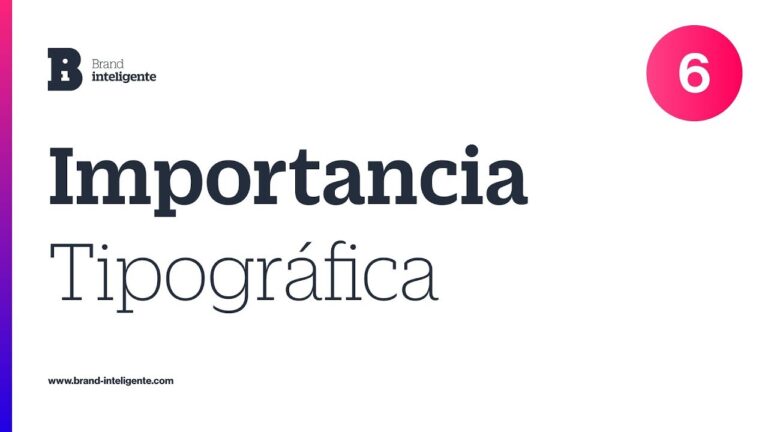
El impacto del diseño gráfico en la tipografía
El diseño gráfico juega un papel fundamental en la comunicación visual, y la tipografía es una de las herramientas más importantes en este campo. En este artículo, exploraremos el impacto que el diseño gráfico tiene en la tipografía, analizando cómo las decisiones de diseño pueden influir en la legibilidad, la estética y la efectividad de un mensaje. ¡Descubre cómo el diseño gráfico y la tipografía se complementan para crear piezas visuales impactantes!
¿Cómo influye la tipografía en el diseño gráfico?
Una tipografía bien escogida mejora la legibilidad, capta la atención del público y contribuye significativamente a la coherencia visual de una pieza de diseño. La elección de la tipografía adecuada puede transmitir emociones, reforzar el mensaje y darle personalidad a la marca o proyecto.
Además, la tipografía puede ser utilizada para jerarquizar la información y guiar al lector a través del diseño, destacando los puntos clave y facilitando la comprensión del contenido. Es importante considerar aspectos como el tamaño, el peso, el espaciado y la combinación de tipografías para lograr un resultado visualmente atractivo y funcional.
En resumen, la tipografía es una herramienta poderosa en el diseño gráfico que va más allá de la simple elección de letras. Su influencia se extiende a la comunicación efectiva, la identidad de marca y la experiencia del usuario, convirtiéndola en un elemento fundamental a tener en cuenta en cualquier proyecto creativo.
¿Qué hace un diseñador tipográfico?
Un diseñador tipográfico se encarga de dar coherencia entre imágenes, texto y formas para crear diseños equilibrados y atractivos. Prestar atención a los detalles y darles forma permite que nuestro mensaje llegue de manera rápida y efectiva a nuestros clientes, mejorando la sensación de confianza en ellos.
¿Qué es la fuente en el diseño gráfico?
La tipografía es la disposición estratégica de los tipos de estilos de letras para hacer que el lenguaje escrito sea legible y visualmente atractivo. El arte de la tipografía es una de las habilidades más importantes que todo diseñador gráfico y web debe dominar.
La influencia del diseño gráfico en la evolución tipográfica
El diseño gráfico ha tenido un impacto significativo en la evolución de la tipografía a lo largo de los años. Desde la invención de la imprenta hasta la era digital, los diseñadores gráficos han experimentado con diferentes estilos y técnicas tipográficas, influenciando directamente la forma en que se utilizan las fuentes en el diseño. La creatividad y la innovación en el diseño gráfico han llevado a la creación de tipografías únicas y modernas que reflejan las tendencias y estilos de la época.
La relación entre el diseño gráfico y la tipografía se ha fortalecido con el avance de la tecnología y la globalización. El diseño gráfico ha permitido que las tipografías evolucionen para adaptarse a las necesidades de la comunicación visual en un mundo cada vez más digitalizado. Los diseñadores gráficos han utilizado la tipografía de manera creativa para transmitir mensajes claros y efectivos, lo que ha contribuido a la evolución y diversificación de las fuentes tipográficas disponibles.
En la actualidad, la influencia del diseño gráfico en la evolución tipográfica es innegable. Los diseñadores gráficos continúan desafiando los límites de la tipografía, explorando nuevas formas de expresión visual y adaptándose a las demandas de un mundo en constante cambio. La evolución de la tipografía está estrechamente ligada al diseño gráfico, y juntos continúan moldeando la forma en que nos comunicamos a través del arte visual.
La intersección entre diseño gráfico y tipografía
El diseño gráfico y la tipografía se entrelazan de manera única en la creación de proyectos visuales impactantes y efectivos. La elección de la tipografía adecuada puede potenciar el mensaje de una pieza gráfica, transmitiendo emociones y reforzando la identidad de una marca. Por otro lado, el diseño gráfico se encarga de organizar y estructurar la información de forma visualmente atractiva, utilizando la tipografía como una herramienta fundamental para lograr un equilibrio y cohesión en el diseño final. Ambas disciplinas se complementan y se potencian mutuamente, demostrando la importancia de la intersección entre diseño gráfico y tipografía en el mundo del diseño visual.
Explorando el poder del diseño gráfico en la creación tipográfica
El diseño gráfico juega un papel fundamental en la creación de tipografías únicas y memorables. Cada letra, cada símbolo, cada espacio en blanco, todo es cuidadosamente diseñado para transmitir un mensaje claro y coherente. La combinación de colores, formas y estilos tipográficos puede impactar de manera significativa en la percepción y la interpretación de la información por parte del espectador.
Explorar el poder del diseño gráfico en la creación tipográfica nos permite adentrarnos en un mundo de creatividad ilimitada. La tipografía va más allá de simplemente transmitir palabras, es una forma de arte que puede evocar emociones, establecer una identidad visual y comunicar la esencia de una marca o un mensaje. Gracias al diseño gráfico, podemos experimentar con diferentes estilos, técnicas y herramientas para dar vida a tipografías innovadoras y atractivas que cautiven a la audiencia.